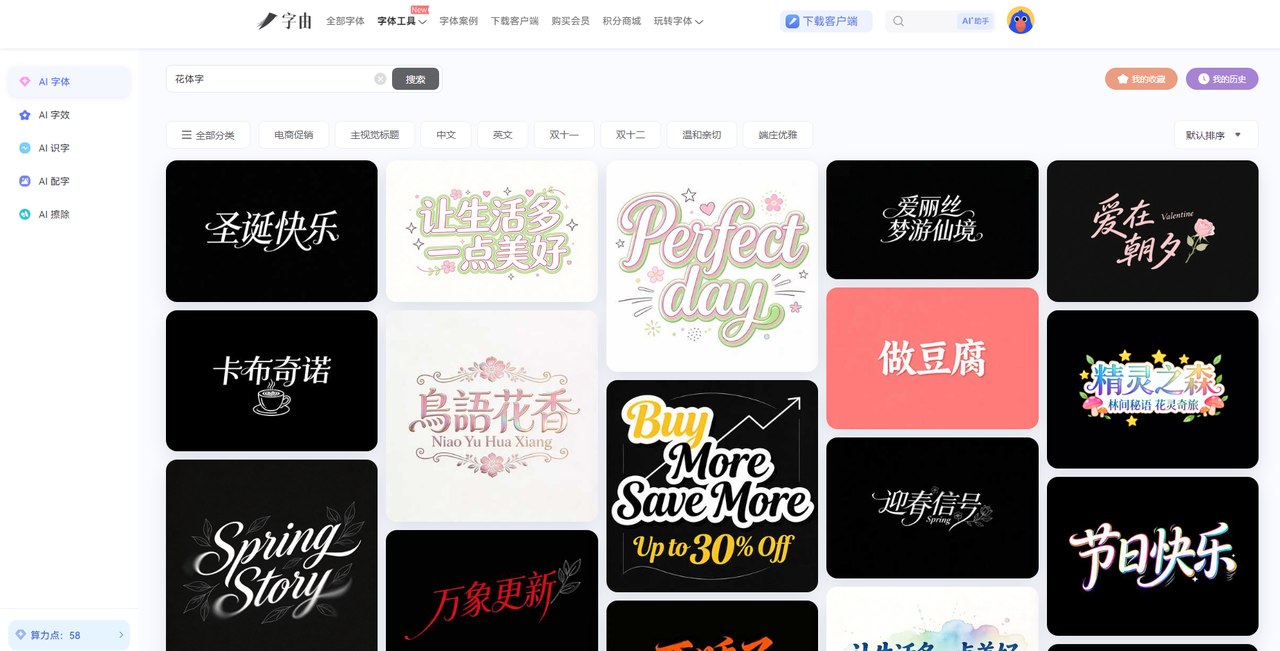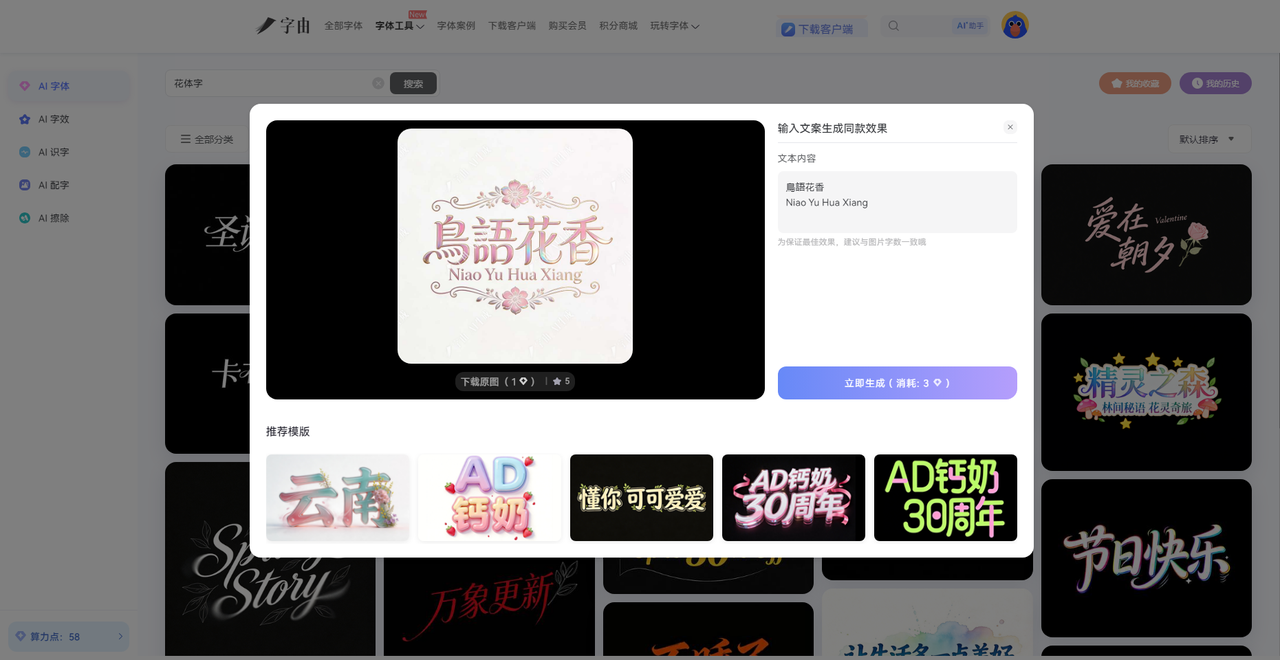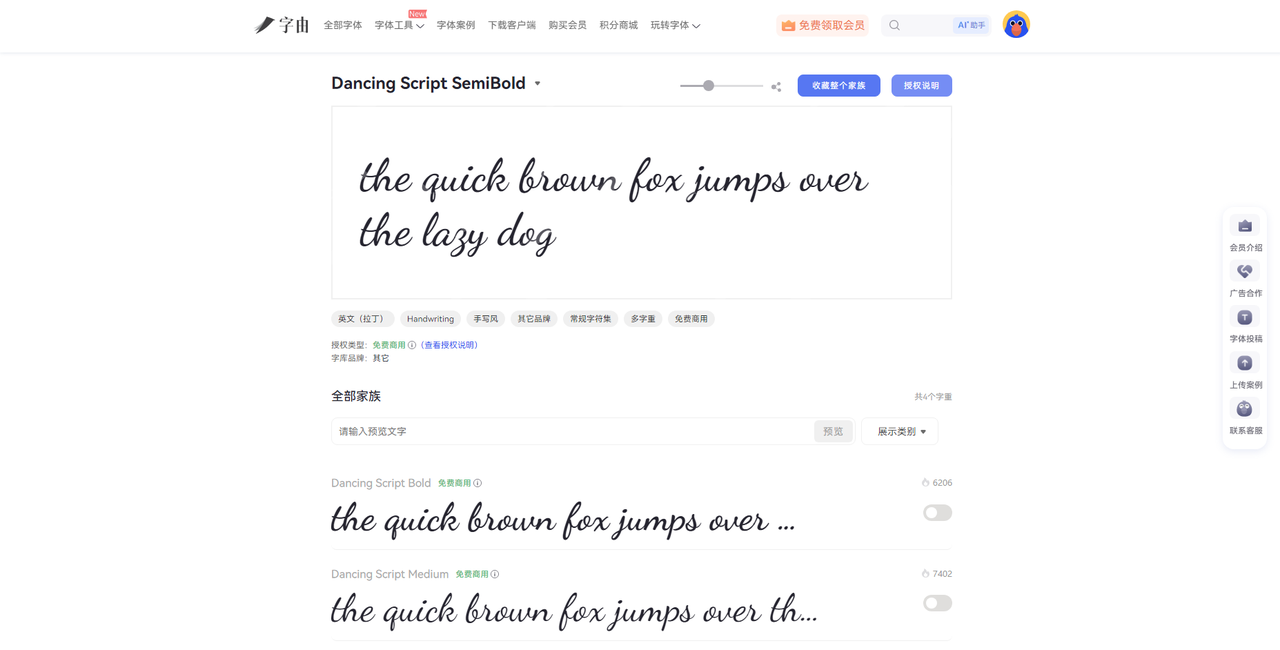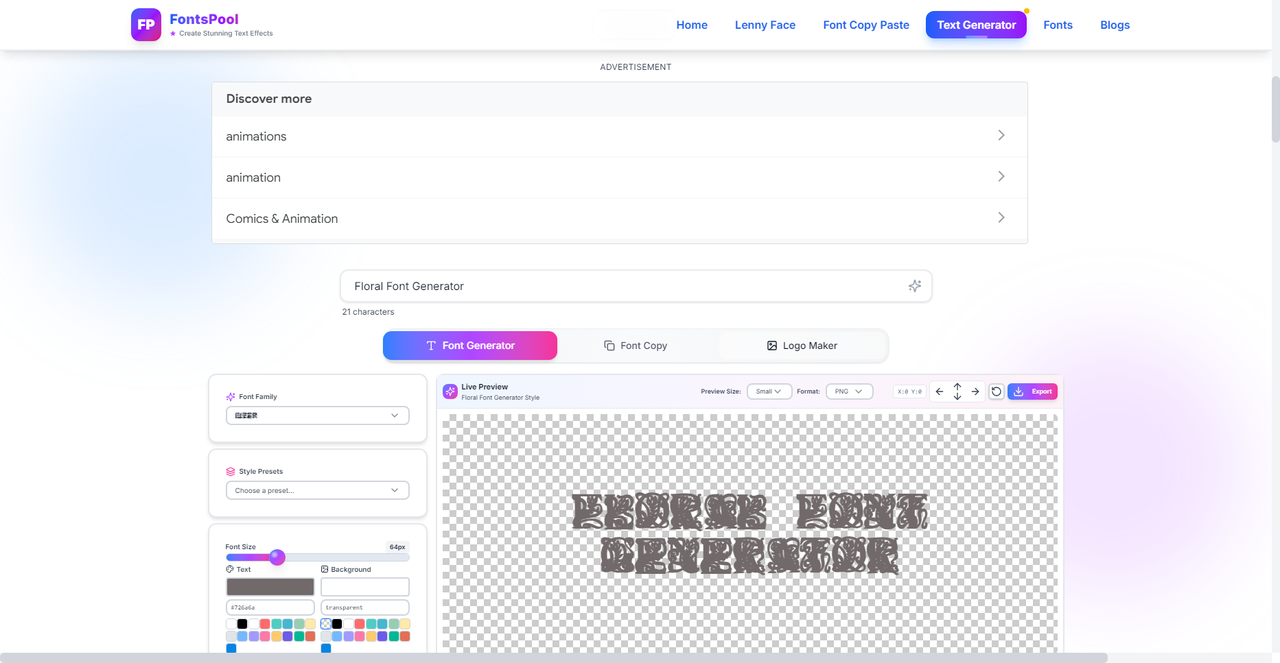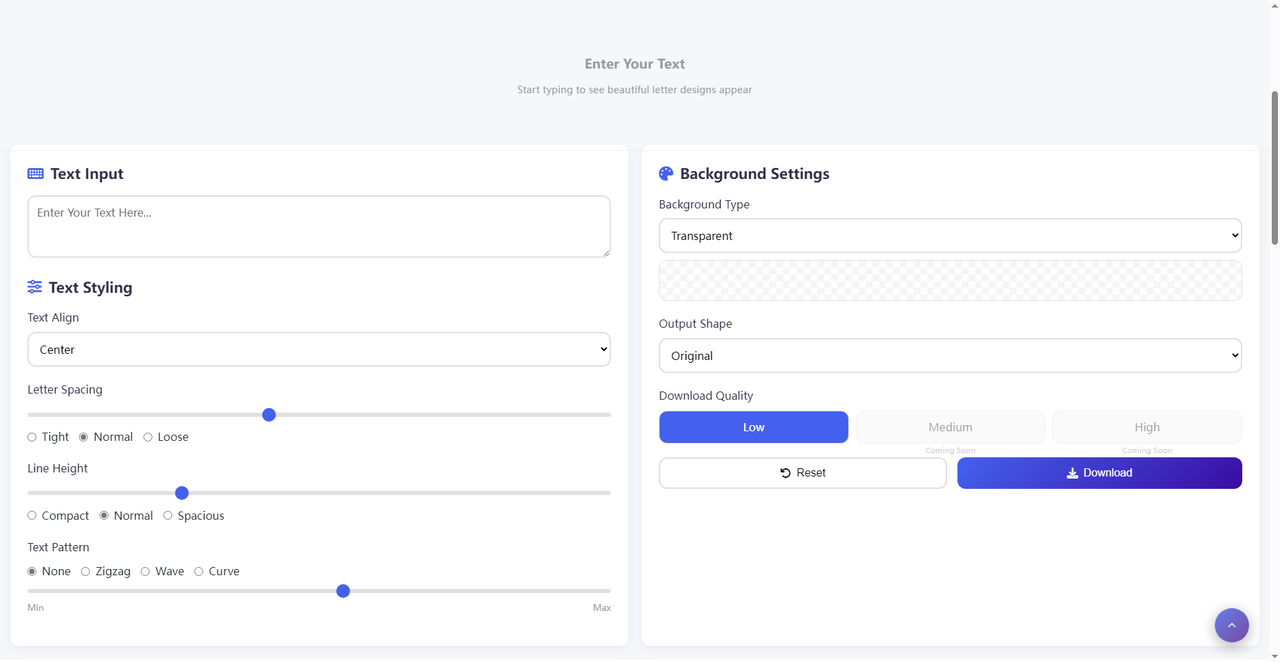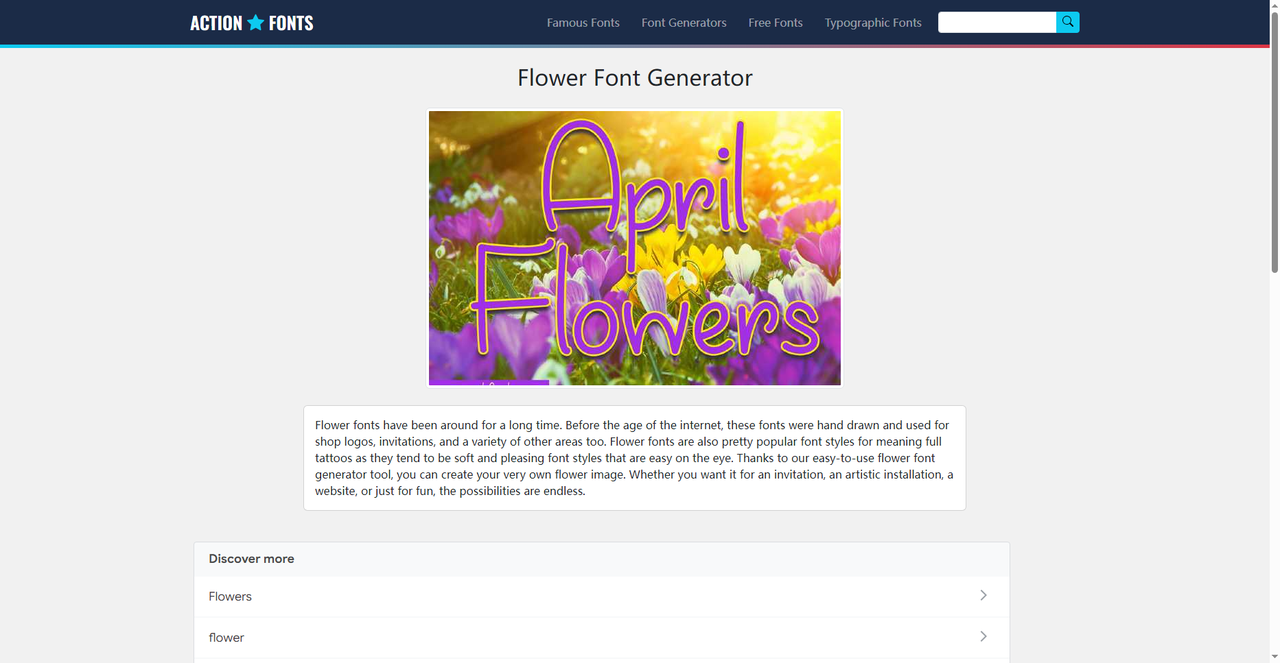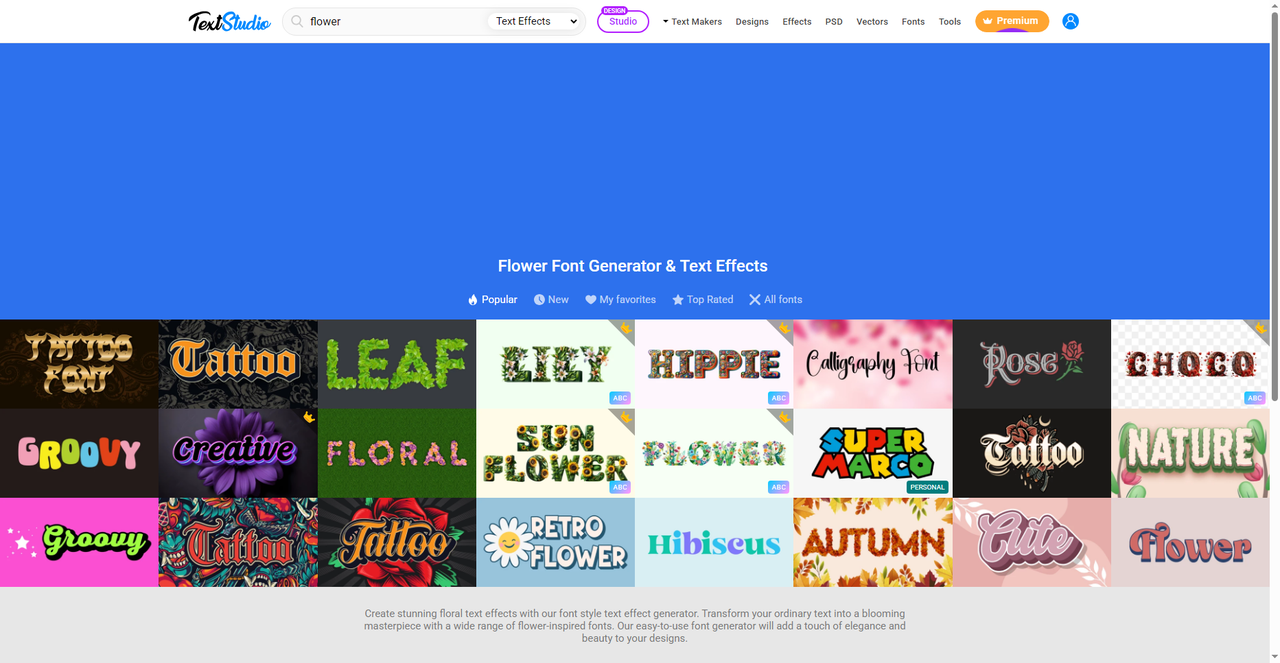
花体字在线转换器推荐,几十种花体样式随便挑
不知道你有没有在别人的设计当中看到那种很优雅很漂亮的花体字,字母像藤蔓一样缠绕,笔画末端开出一朵小花,看着就很精致。又或者刷到婚礼请柬上的英文花体字,优雅又浪漫,自己也想要同款,但不知道去哪弄。以前想要这种效果,要么自己慢慢画,要么花钱请设计师。现在简单了,用花体字在线转换器,输入文字,选个风格,点一下,几十秒就能拿到带花朵装饰的艺术字。今天我就重点介绍一个我常用的几个花体字在线转换器,需要的可以收藏。
字由的AI字体工具可以完美地帮我们解决这个问题,它能够生成花体风格的艺术字。你不需要下载任何字体,也不用装软件,打开网页就能用。下面我会介绍详细的使用步骤:
• 打开字由官网或客户端,进入【AI字体】页面。在搜索框里输入“花”“花朵”“装饰”“浪漫”“英文花体”这些关键词,系统会自动筛出带有花体风格的模板。
• 比如我搜“flower”,出来好几个模板,有的字母带着藤蔓装饰,有的字母顶端有小花,有的整体像手写的英文草书。每个模板都有预览图,鼠标放上去就能看到效果。
• 选一个顺眼的模板,点击“做同款”,把模板里的英文换成你自己的文字。注意最好和模板的字数保持一致,字母数量差不多,生成的效果最自然。
• 点击“立即生成”,等20-30 秒,就能拿到一张高清的艺术字图片。下载时选透明背景,直接拖进PS、Canva、剪映里用。不用抠图,不用调色。
除了AI生成,字由本身的免费商用字体库里也有很多花体字。打开“全部字体”,在字体类型里选“手写体”或者“英文花体”,就能看到一大片。比如“Great Vibes”这种经典英文花体,流畅优雅,适合做婚礼请柬的主标题。“Pacifico”是那种圆润可爱的花体,适合做品牌Logo。“Dancing Script”带点跳跃感,用在社交媒体封面上很吸睛。
所以字由在“花体字”这件事上,给了两个选择:一是用AI直接生成带特效的花体艺术字,二是用字体库里的现成花体字自己排版。两条路是都免费的。
2、Floral Font Generator
这个网站名字就叫 Floral Font Generator,是一个专门生成花体字的工具。它提供了13 种花体风格,每个风格都是字母带着花朵或植物装饰。进入页面后,你可以在输入框里打字,下面会实时预览效果。可以调整字体大小、背景颜色,还能选透明背景。下载时支持4K高清导出,完全免费。我试了其中几个风格,有的像藤蔓缠绕,有的像花瓣拼成,有的很复古,有的很小清新。用它做个英文名字的Logo,或者做邀请函的标题,效果都不错。
它还有一个“Logo Maker”功能,可以直接把生成的花体字做成Logo,调整布局和配色。虽然功能不算多,但胜在简单直接,上手零门槛。
3、EXCPIX Flower Text Maker
这个网站叫EXCPIX,里面的“Flower Text Maker”功能非常强大。它不只是生成花体字,还能精细调节文字的每一个细节。输入文字后,你可以调整以下细节:
• 背景类型(透明、纯色、渐变)
• 文字对齐方式
• 输出形状(原始、圆形、弧形等)
• 字母间距、行高
• 文字排列模式(直线、Z字形、波浪、曲线)
• 下载质量(低、中、高)
它还提供了很多预设效果,比如“BROCCOLI”“AULER”“PEARL”“DARK”“PUMPKIN”等,点一下就能看到不同的花体风格。如果你想要完全控制生成效果,这个工具很适合。比如你想让文字沿着一条波浪线排列,选“Wave”模式就行。想让它像花环一样围成圆形,选“Curve”再调弧度。生成后可以下载高清图片,分享到社交媒体。完全免费,不用注册。
4、ActionFonts Flower Font Generator
这个网站来自 ActionFonts,它的Flower Font Generator 可以让你生成带有真实花朵图案的字体。操作很简单:输入文字,选择字体名称(比如“AlphaFlowers”),调整字体大小、文字颜色、背景颜色,点击生成。它会把你输入的文字,每个字母都用花朵图案拼出来。比如你输入“LOVE”,生成的图片里,L是一朵花,O是一朵花,V是一朵花,E也是一朵花。每个字母都变成了不同颜色的小花,特别适合做春天主题的海报、儿童活动邀请函、花卉展览宣传。它还支持无限次生成,完全免费。如果你需要那种“字就是花”的效果,这个工具很好用!
5、TextStudio Flower Font Generator
最后一个工具是TextStudio,它的Flower Font Generator提供了几十种花体样式。首页展示了很多预设,比如:
• Tattoo LEAF(叶子纹身风格)
• HAPPY HIPPIE(快乐嬉皮风)
• Calligraphy Font Rosé(玫瑰书法)
• CHOCO(巧克力风格)
• GROOVY Creative(复古创意)
• FLORAL FLOWER(花卉装饰)
每种风格点进去,输入文字就能生成对应的效果。有的风格是字母带叶子,有的是字母带花瓣,有的是整体做成花朵形状。生成后可以下载PNG,也可以下载矢量文件(AI/EPS),方便后期编辑。TextStudio 的优点是风格多、更新快,而且每个风格都有预览图,不用一个个试。适合想要快速找到合适风格的用户。
以上介绍的这几个花体字在线转换器都有着非常强大并且实用的功能,但字由是我用得最多的,也算是我用得最频繁的一个花体字在线转换器,它胜在最全面——既能用AI生成花体艺术字,又有海量免费商用的花体字体库,还能一键应用到设计软件里。而且完全免费,没有水印,如果你也想要那种优雅、浪漫、带花朵装饰的花体字,不妨从字由开始试试。